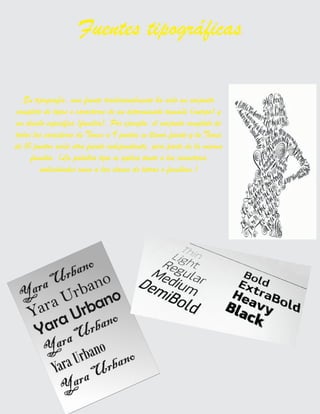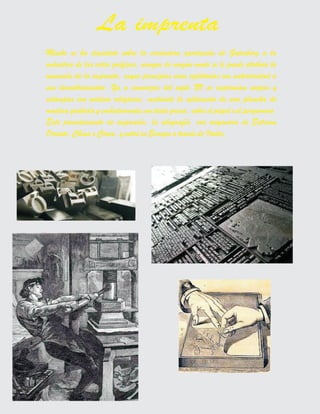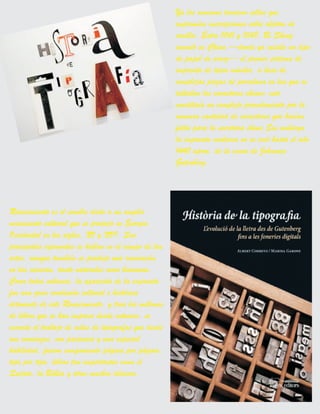
Tipografía,
Tipos Y Anotomía
La Tipografía resulta ser el arte y la técnica de impresión a
través de formas con relieve que reciben el nombre de tipos,
los cuales, hechos de plomo, una vez entintados serán
aplicados sobre el papel para así obtener un trabajo de
impresión, ya sea un documento, un texto, entre otros
materiales.
Definición de tipografía
La palabra tipografía de origen griego tipos ( golpe - huella ), hace referencia a un arte y una técnica
que consiste en el manejo y la composición de tipos, originalmente hechos de plomo, para comunicar un
mensaje mediante un impreso.
La tipografía tiene muy antiguos orígenes, que están relacionados con la caligrafía y los manuscritos,
que ya eran usados antes del año 2500A.C.
Durante toda la edad media la "industria editorial" se centraba en los monasterios donde los libros eran
copiados a mano por monjes especializados, llamados copistas; esta labor se hacia en el scriptorium, el
donde se copiaban los textos.
Posteriormente con el invento de la imprenta, en la época del renacimiento, la tipografía tomo una
especial relevancia. En esta época Johanes Gutembreg imprimió su biblia de 42 líneas utilizando sin
embargo, caracteres del periodo gótico.
Ya hacia el año de 1500 D.C. la imprenta se había difundido de forma exponencial, la técnica había
tenido tanta difusión que en Europa ya existían alrededor de 1100 imprentas instaladas y en
funcionamiento.
Este auge de los tipos móviles, permitio un gran desarrollo a la producción de materiales impresos los
cuales utilizaban tipografías como la minúscula carolingia y a las mayúsculas cuadradas romanas;
adaptadas de los caracteres e inscripciones encontrados en las ruinas del imperio romano
Estas fueron entre otras, las primeras tipografías romanas, clásicas o con serifa. Llamamos serifas a
las pequeñas extensiones o adornos que pueden llevar los caracteres tipográficos.
La primera tipografía con serifas apareció en el año de 1465, posteriormente se estilizaron sus líneas y
se dio origen a la llamada bastardilla, similar a los que actualmente conocemos como itálica
Origen de la tipografía
Ya los romanos tuvieron sellos que
imprimían inscripciones sobre objetos de
arcilla. Entre 1041 y 1048, Bi Sheng
inventó en China —donde ya existía un tipo
de papel de arroz— el primer sistema de
imprenta de tipos móviles, a base de
complejas piezas de porcelana en las que se
tallaban los caracteres chinos; esto
constituía un complejo procedimiento por la
inmensa cantidad de caracteres que hacían
falta para la escritura china.Sin embargo,
la imprenta moderna no se creó hasta el año
1440 aprox. de la mano de Johannes
Gutenberg.
Renacimiento es el nombre dado a un amplio
movimiento cultural que se produjo en Europa
Occidental en los siglos, XV y XVI. Sus
principales exponentes se hallan en el campo de las
artes, aunque también se produjo una renovación
en las ciencias, tanto naturales como humanas.
Como todos sabemos, la aparición de la imprenta
fue una gran revolución cultural e histórica
detonante de este Renacimiento, y tras los millones
de libros que se han impreso desde entonces, se
esconde el trabajo de miles de tipografos que desde
sus comienzos, con paciencia y una especial
habilidad, fueron componiendo página por página,
tipo por tipo, libros tan importantes como el
Quijote, la Biblia y otros muchos clásicos.
Este término hace referencia a la proporción que mantienen las letras, sin
embargo no hay que olvidar que existe una variante y una similitud entre todas
las familias tipográficas
1. El ojo de la letra.
2. La línea base de escritura.
3. La altura de bloque.
4. El ancho del tipo.
5. El cran, o ranura de posición.
6. El cuerpo.
7. La altura de impresión
Origen y Anatomía del tipo
Tipos Renacentistas Los tipos renacentistas
abarcan un amplio espacio cronológico, que va
desde los creados por los primeros impresores
venecianos a mediados del siglo XV, hasta los
desarrollados a partir de ellos por los
punzonistas franceses del siglo XVI. En su
evolución podemos apreciar dos estadios
claramente diferenciados.
Tipos Barrocos En esta categoría englobamos
principalmente a los tipos creados en los Países
Bajos durante el siglo XVII y que tiene por
protagonistas a los punzonistas Reinhard
Voskens y Christoffel Van Dijck.
tipos Neoclásicos Al amparo de los nuevos
tiempos auspiciados por la Ilustración y la
Enciclopedia, se procede a racionalizar y
sistematizar los conocimientos de las ciencias y
las artes que existían en la época.
Tipos Románticos El desarrollo estilístico de
El prototipo deesta tipografía fue diseñada por Herbert Bayer, profesor de la famosa escuela Bauhaus en Dessau, Alemania, en el año 1925 en su labor de crear una tipografía Universal. Su diseño responde a las convicciones y estilo propio de la escuela, buscando la funcionalidad en la eliminación de elementos dejando la tipografía en su apariencia más elemental. Edgard Benguiat junto con Victor Caruso redibujaron la tipografía en 1975 para la ITC. El resultado fue una letra compuesta de formas geométricas, muy simple y monótona, reflejando el estilo de la época pero que no pasó la prueba del tiempo perdiendo la universalidad y objetividad que pretendía. Puede ser usada en diseños con reminiscencias de los años 20 y en la época del Art Decó con líneas simples, limpias y contraformas sin cerrar. La bahuaus tipografica Tipografía del siglo xx examina los principales aspectos que han dado forma a la historia del diseño tipográfico y, en los últimos tiempos, también del diseño gráfico. El libro muestra de qué modo las actuales corrientes tipográficas forman parte de un continuo proceso de cambio que se va tejiendo a lo largo de las diferentes décadas. Entre los temas tratados se encuentran la llegada de la producción de masas, el surgimiento de la figura del director de arte, la aparición de la retícula (y su posterior abandono), la llegada de los medios no impresos y el lanzamiento de los Macintosh, con la consiguiente aparición de una nueva generación de diseñadores que han visto cómo la tecnología digital facilita su modo de trabajo. La tipogrfia del siglo xx